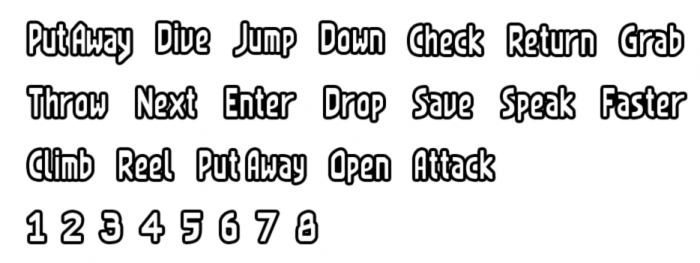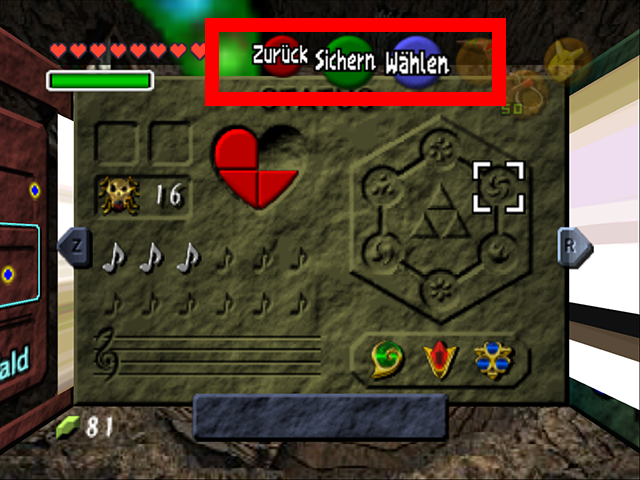
Schriftart von "Legend of Zelda: Ocarina of Time", Aktionsbuttons
Ich suche eine spezifische Schriftart, die ich mit den gängigen font identifiers wie whatthefont oder whatfontis usw. nicht gefunden habe.
Google hat mir auch nicht weiter geholfen. Entweder hat noch nie jemand nach dieser Schrift gesucht oder es gibt sie nicht.
Es geht um eine Schriftart, die im Nintendo 64 Videospiel "The Legend of Zelda: Ocarina of Time" für die Aktionsbuttons ("A"-, "B"- und "Start"-Knopf) verwendet wird.
Also nicht die Schrift für Dialoge und Ortsbezeichnungen (das ist die "Chiaro", falls das jemand wissen möchte).
Was die Schrift auszeichnet, sind die schmalen Buchstaben und ein wiederkehrender Nordost-Südwest Winkel à 45°. Gut sichtbar bspw. an den Buchstaben "P", "v", "J", "b", "O".
Ich habe eine Referenzgrafik angehängt.
Es ist möglich, dass es die Schrift nicht gibt, und diejenige Person, die die Texte ins Spiel integriert hatte, die Buchstaben gezeichnet und keine verwendet hat. Ein Hinweis darauf sind die zwei "A"-Varianten in "Away".
Ich hänge ausserdem noch einen Screenshot aus dem Videospiel an. Im roten Kasten befindet sich die Schriftart in Aktion. Allerdings sehr pixelig und in niedriger Auflösung, aber die Schrift ist dieselbe (oder ihr sehr ähnlich).
Was ich suche ist entsprechend exakt diese Schrift, sofern sie existiert. Oder dann eine möglichst ähnliche mit ähnlicher Breite und jenem 45° Winkel.
Nachtrag: Ich habe jetzt eine andere Schrift gefunden, die mir recht zusagt: "Not sure if weird or just Regular". Eine lizenzfreie Schrift, die auf myfonts nicht zu finden ist, weshalb ich sie nicht einbinden kann. Sie lässt sich aber leicht googlen. Eignet sich sehr gut für meine Zwecke.